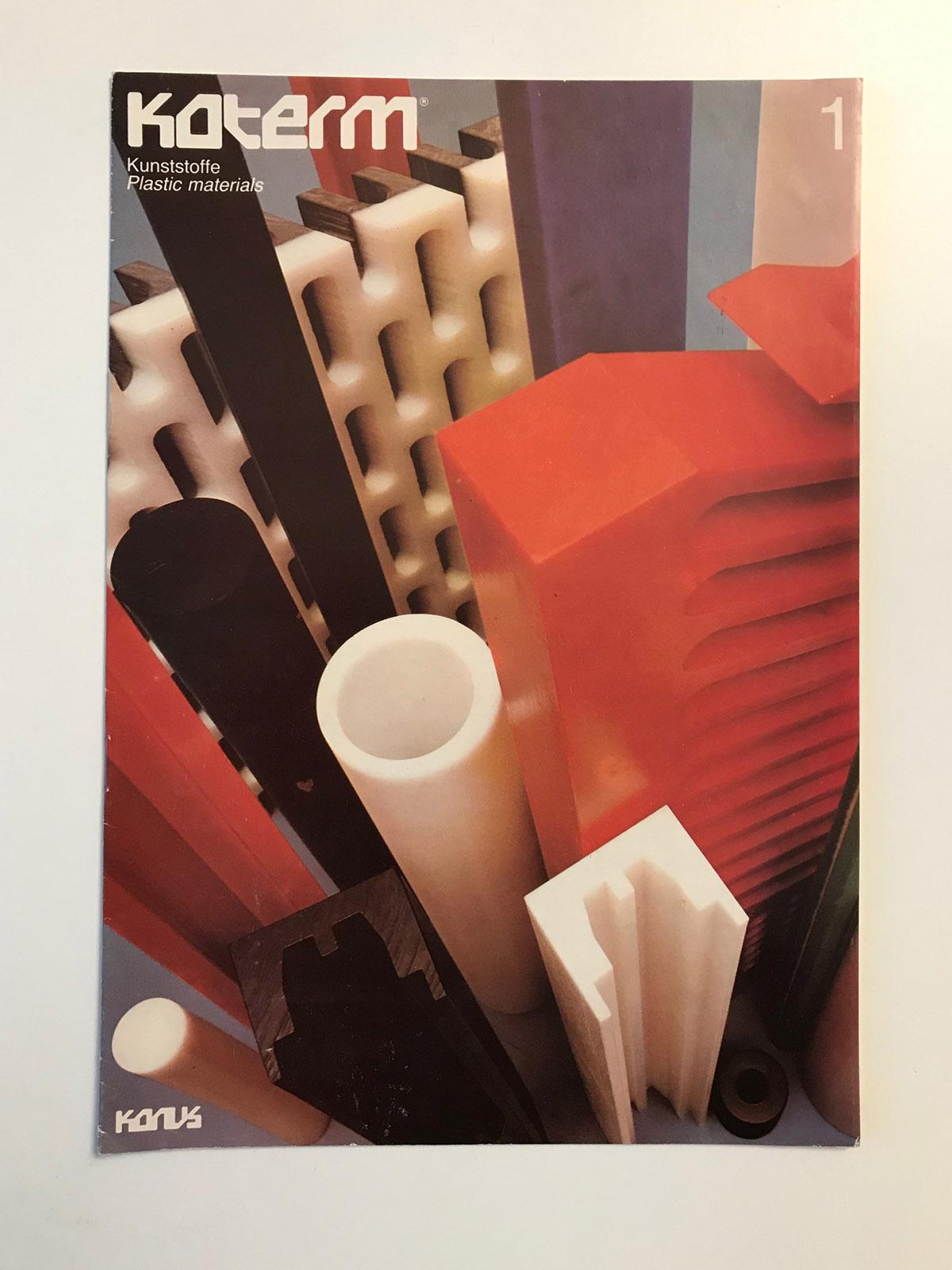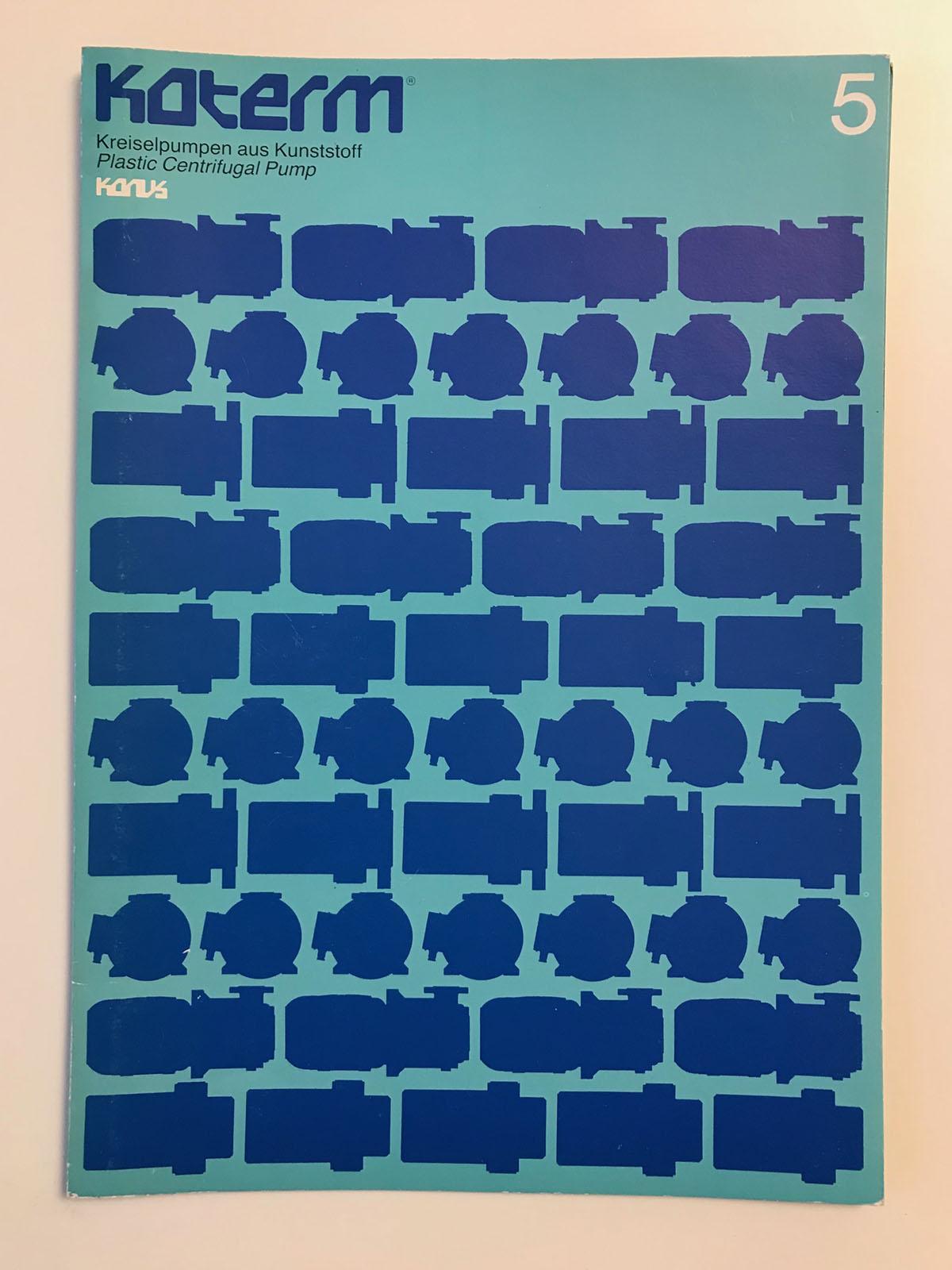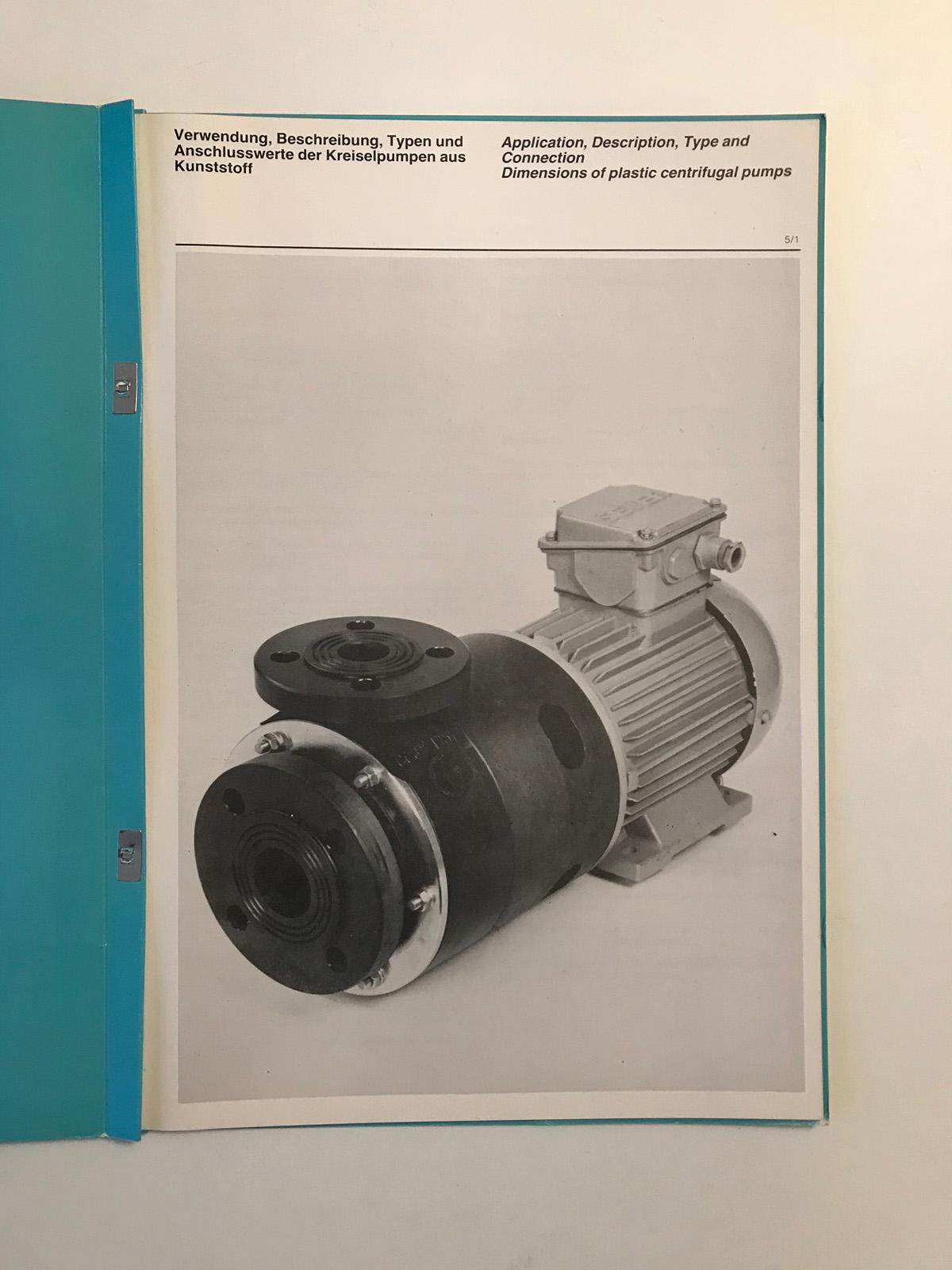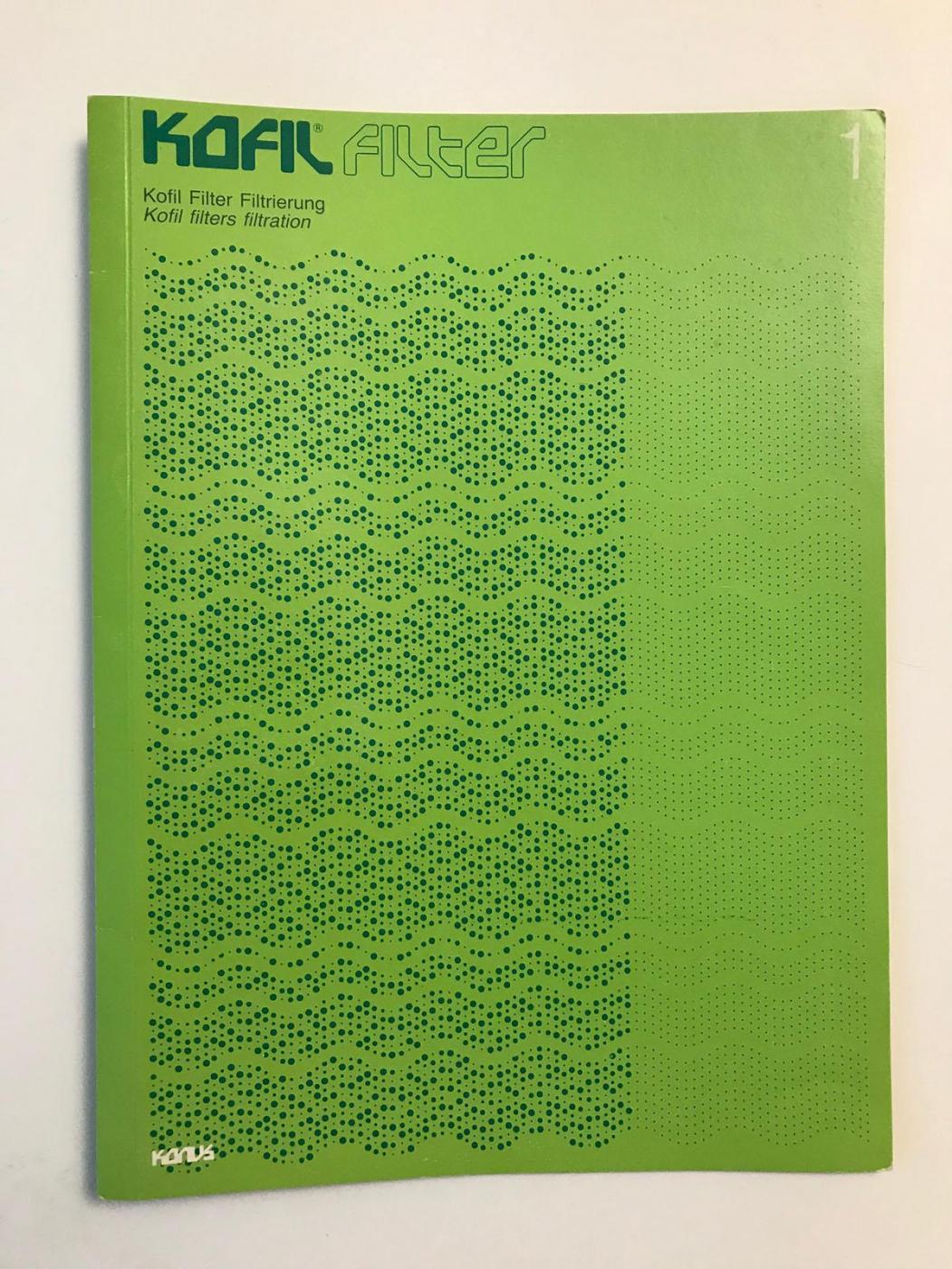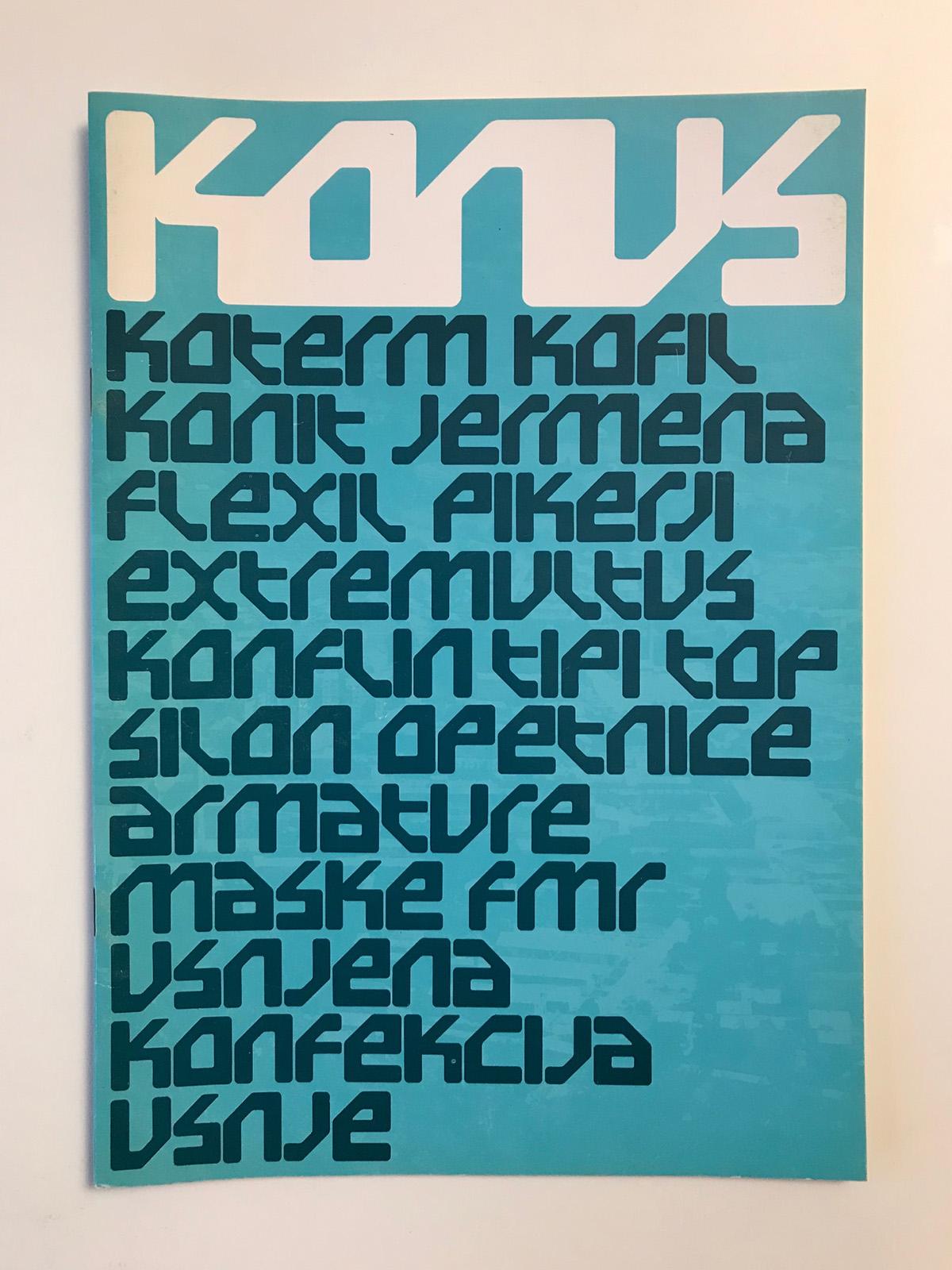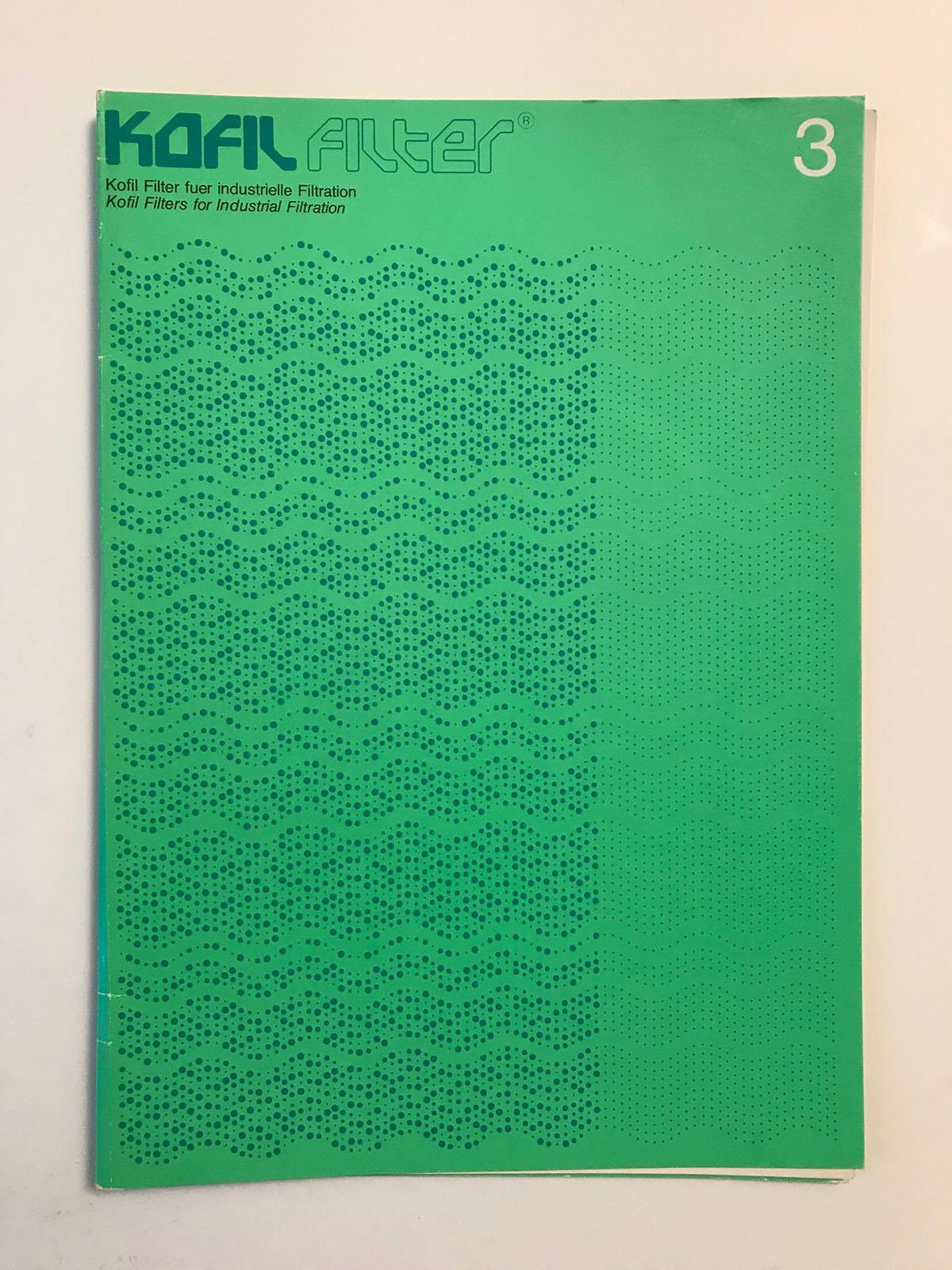
Heute fielen mir beim Aufräumen einige Broschüren in die Hände die ich euch nicht vorenthalten will. Ich habe keine Ahnung woher ich die Teile habe und von wann sie sind. Ich schätze aber 1970er oder 1980er Jahr ...
Ich diskrimiere grundsätzlich nicht. Wenn ich es aber täte, dann wäre dies für mich die häßlichste Schrift, die ich je gesehen habe!
Und dann, ich glaube in den 1980er Jahren erfolgte die Umstellung auf Tetrapack. Hier behaupteten die Hersteller, dass die Eindickung der Milch mit einem schonenderen Verfahren bei verringertem Druck erfolgt. Trotzdem stimmte irgend etwas nicht, die Kondensmich aus den Tetrapaks war bräunlich beige, und hatte diesen H-Milch-Geschmack, nur eben noch mal deutlich extremer.
Ich habe das selbst vor knapp 15 Jahren zu ersten Mal erlebt. Eine Offenbarung! :biglove: